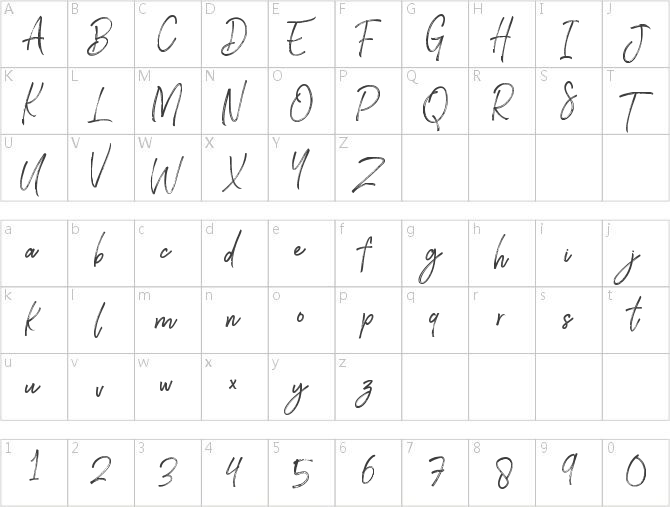
Brownhill Script
Brownhill Script介紹
Brownhill Script字體Brownhill Script Regular字庫是一款讓人賞心悅目、百看不厭的英文字體,適合各類廣告和產品包裝設計應用,字體大小0.68MB,格式為otf字體,上傳用戶是后天的昨天,作者/版權方為Brownhill